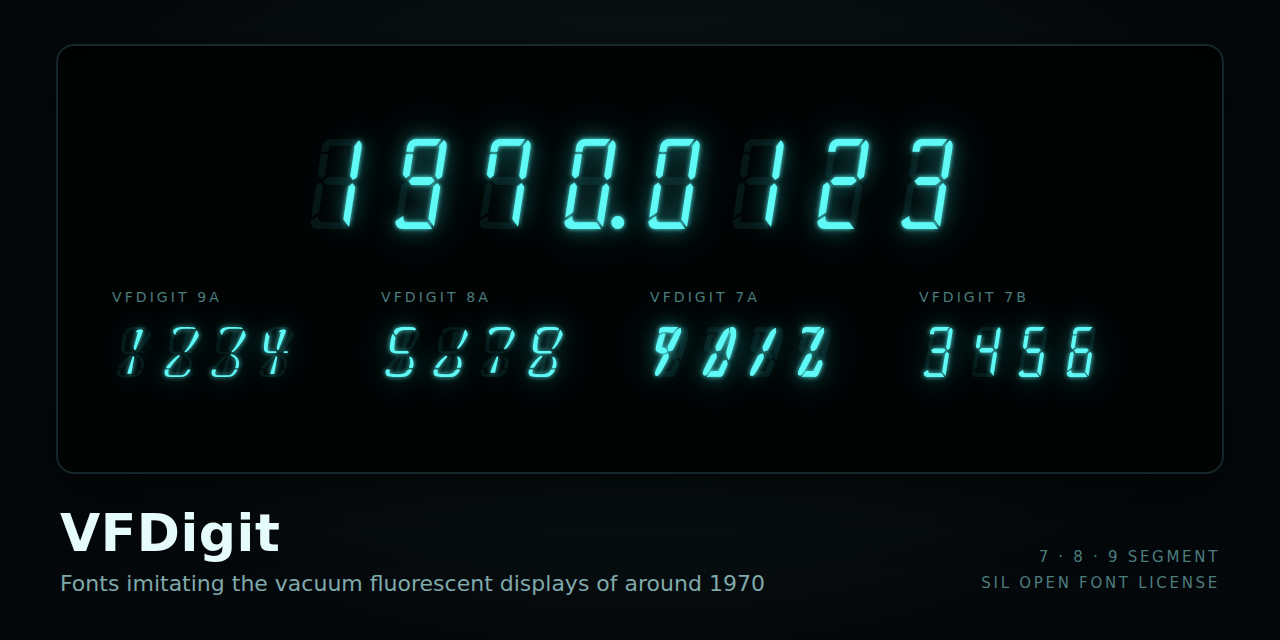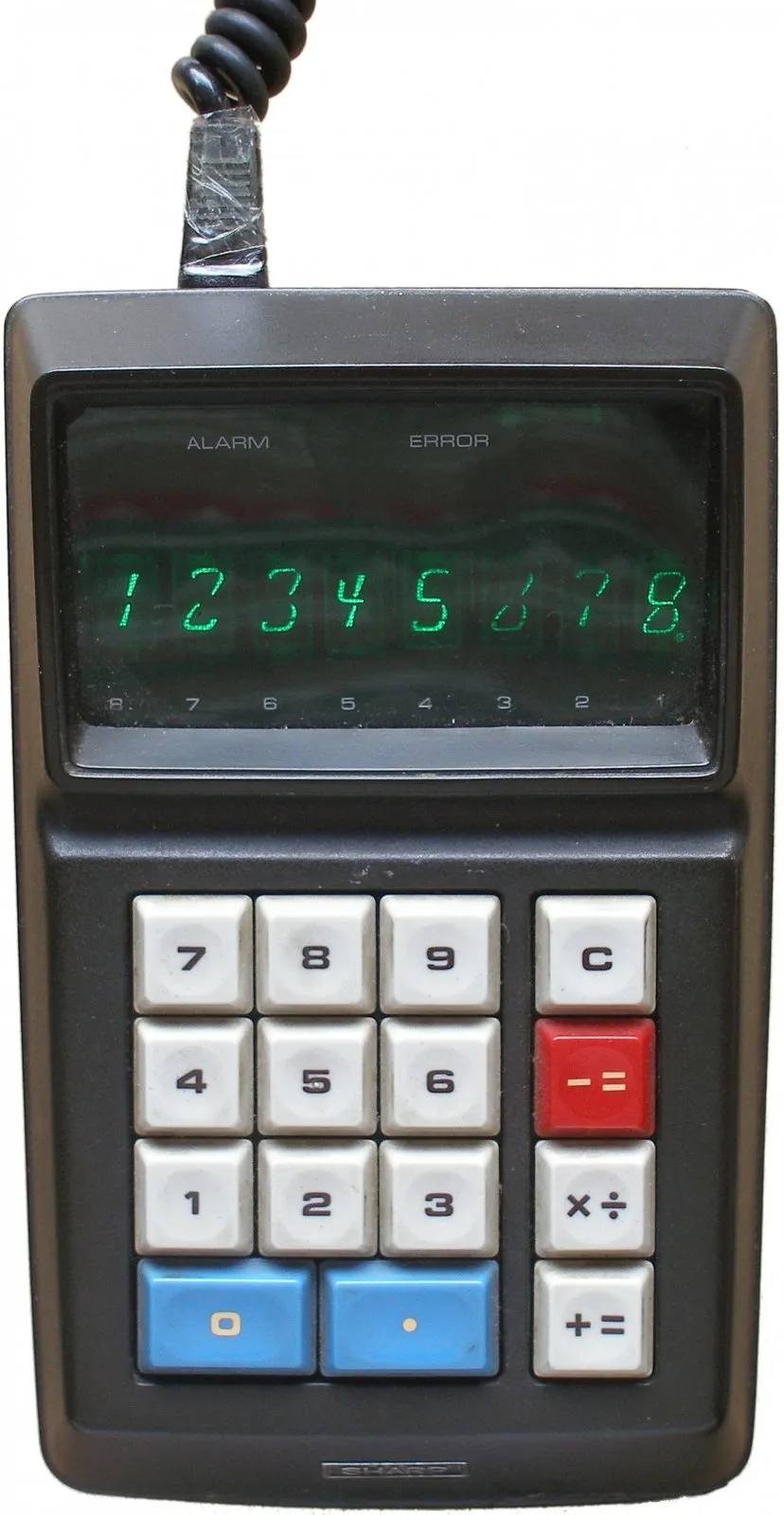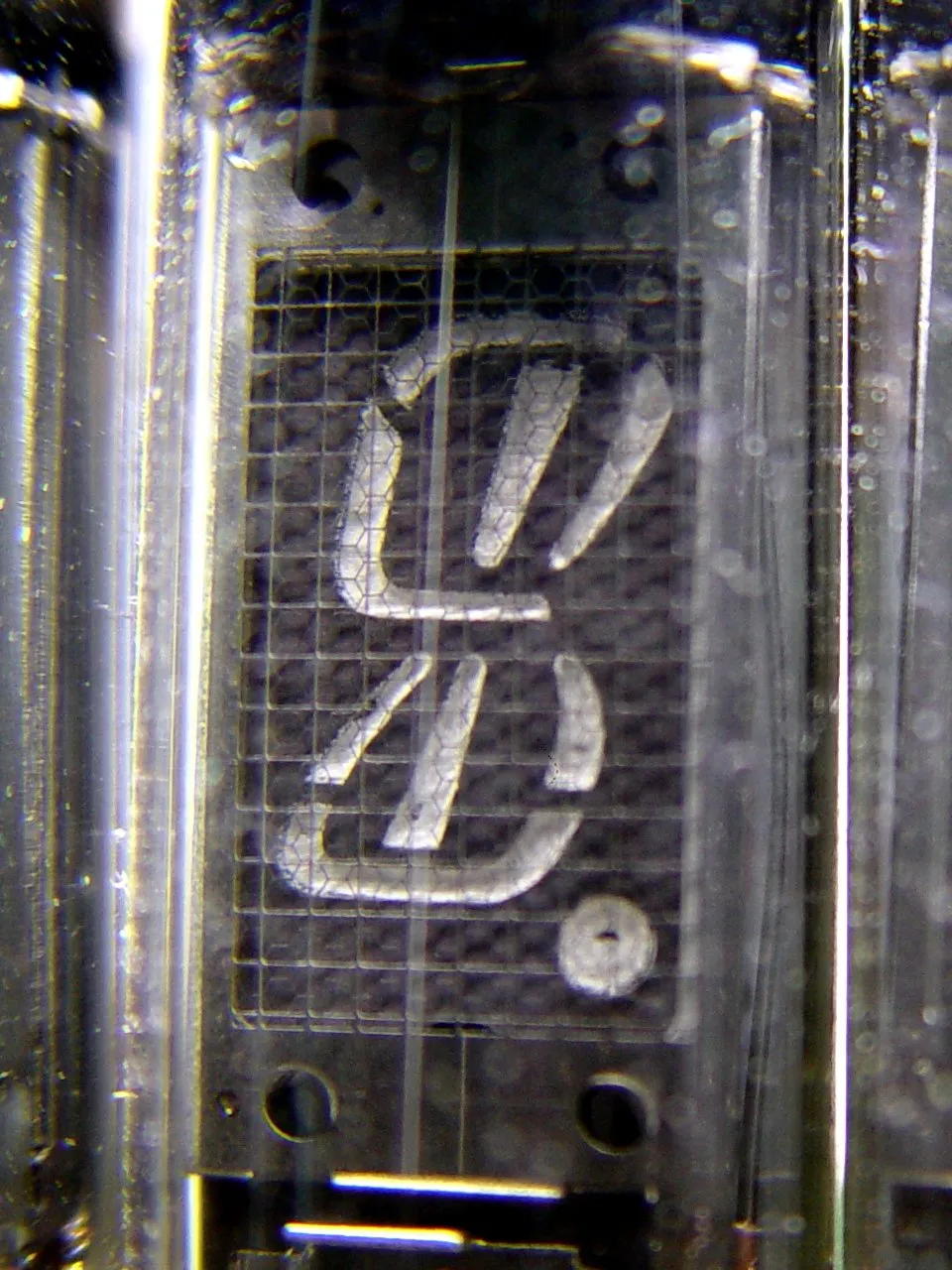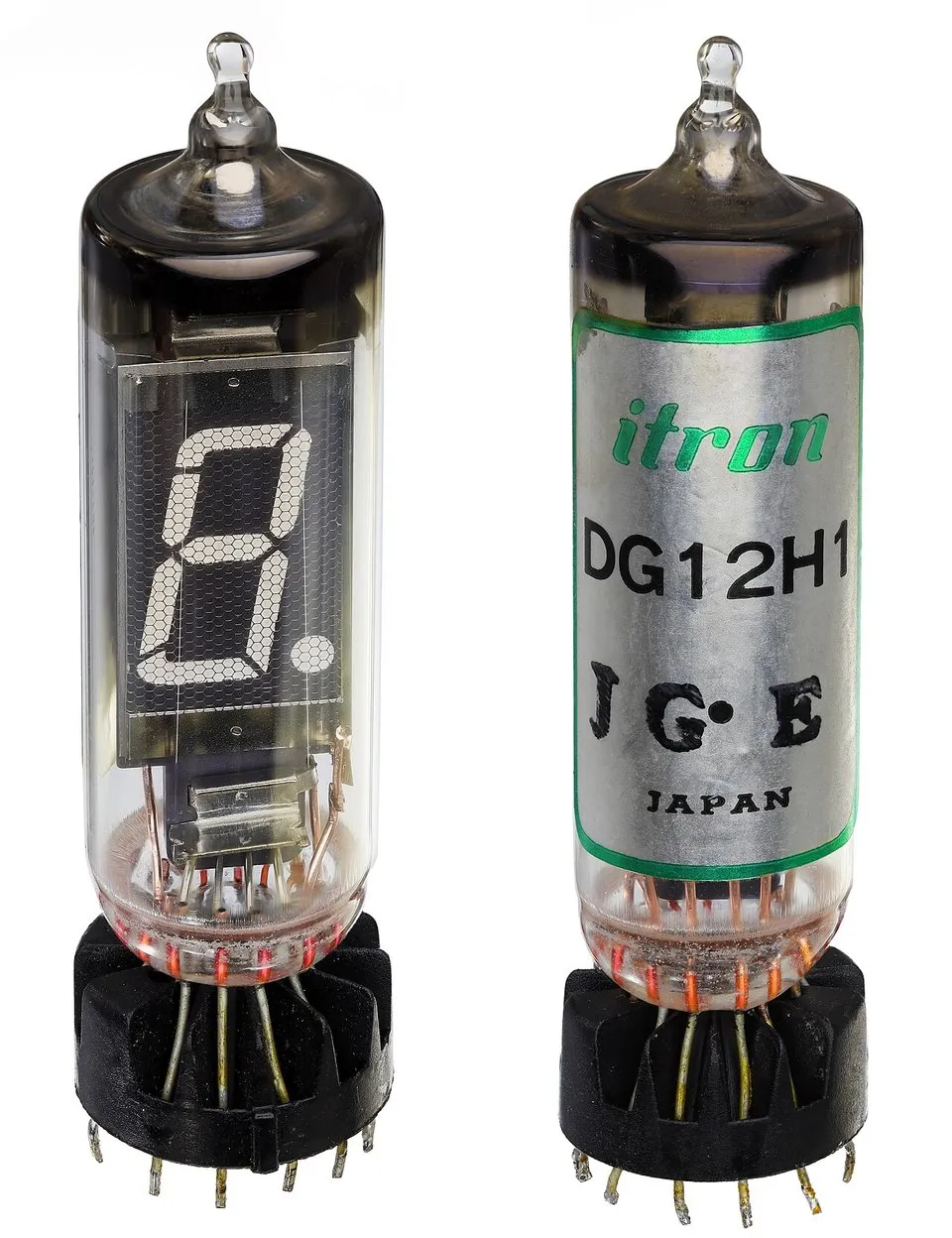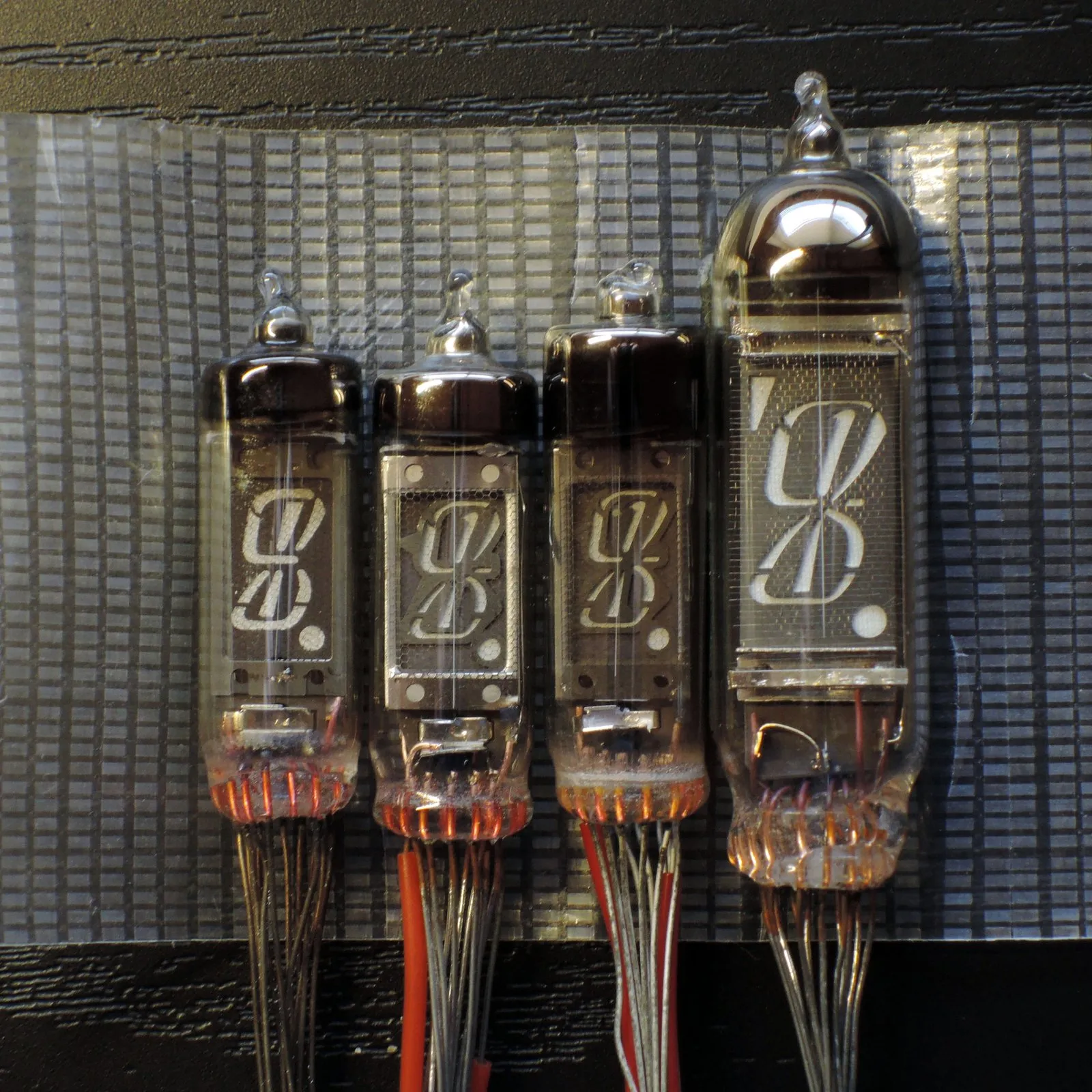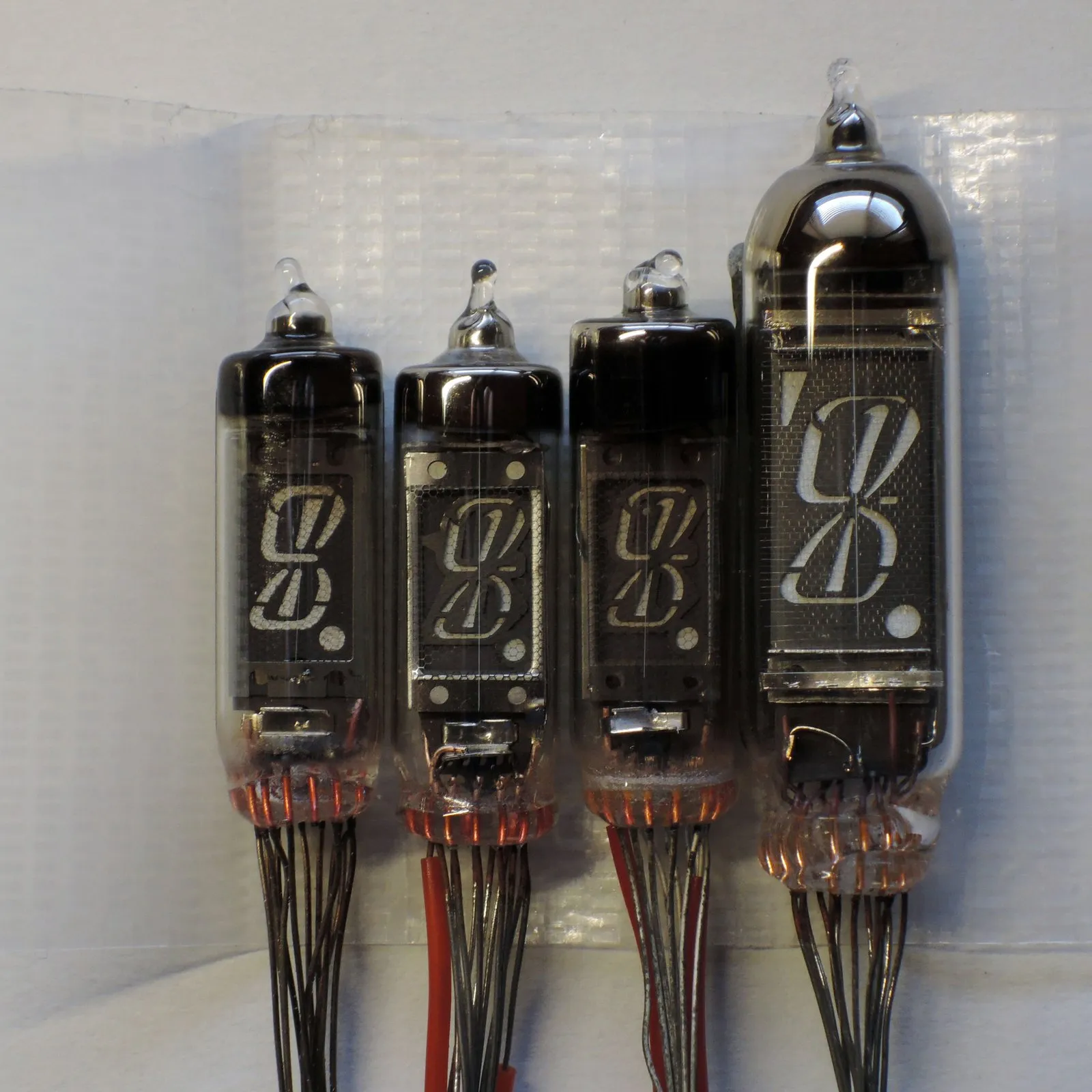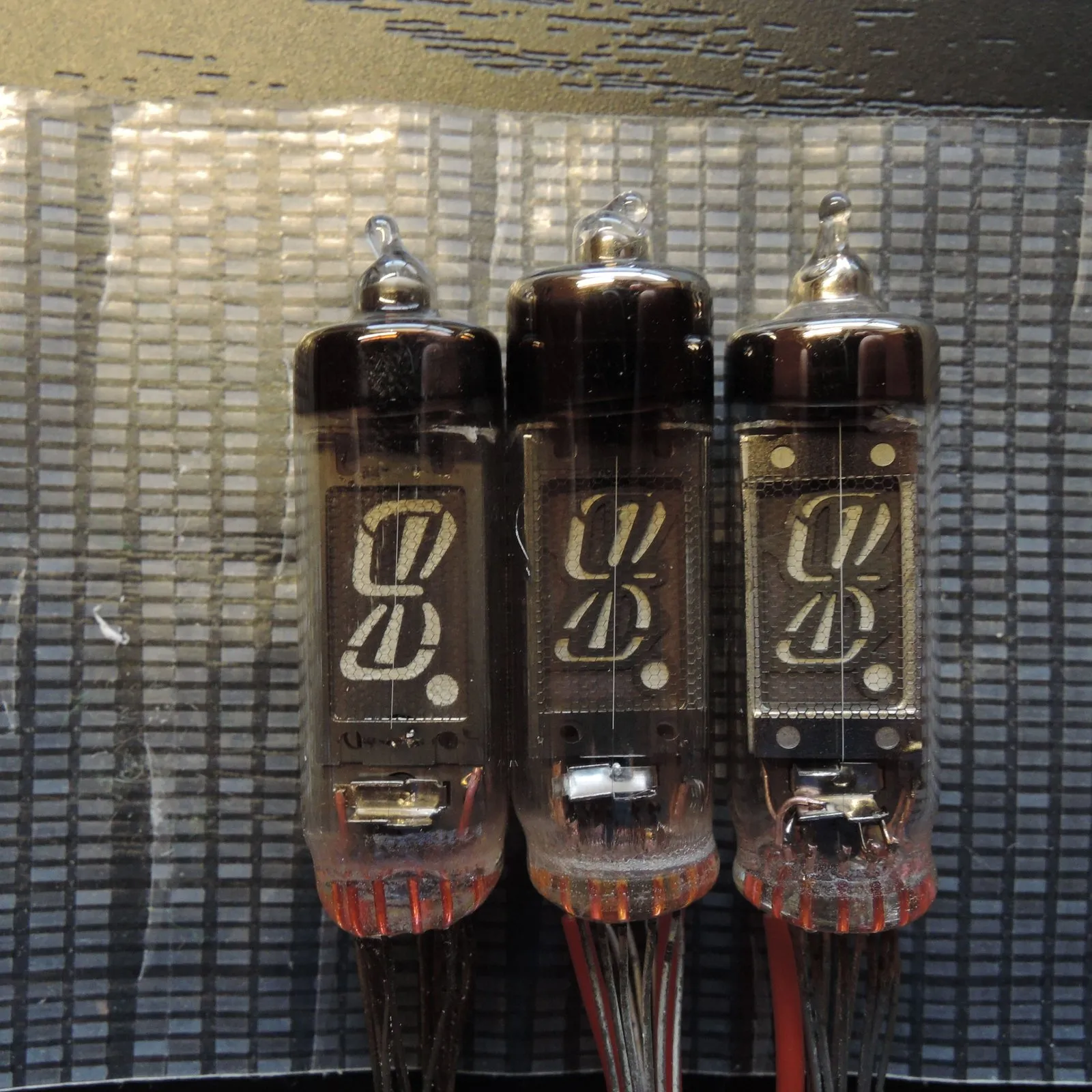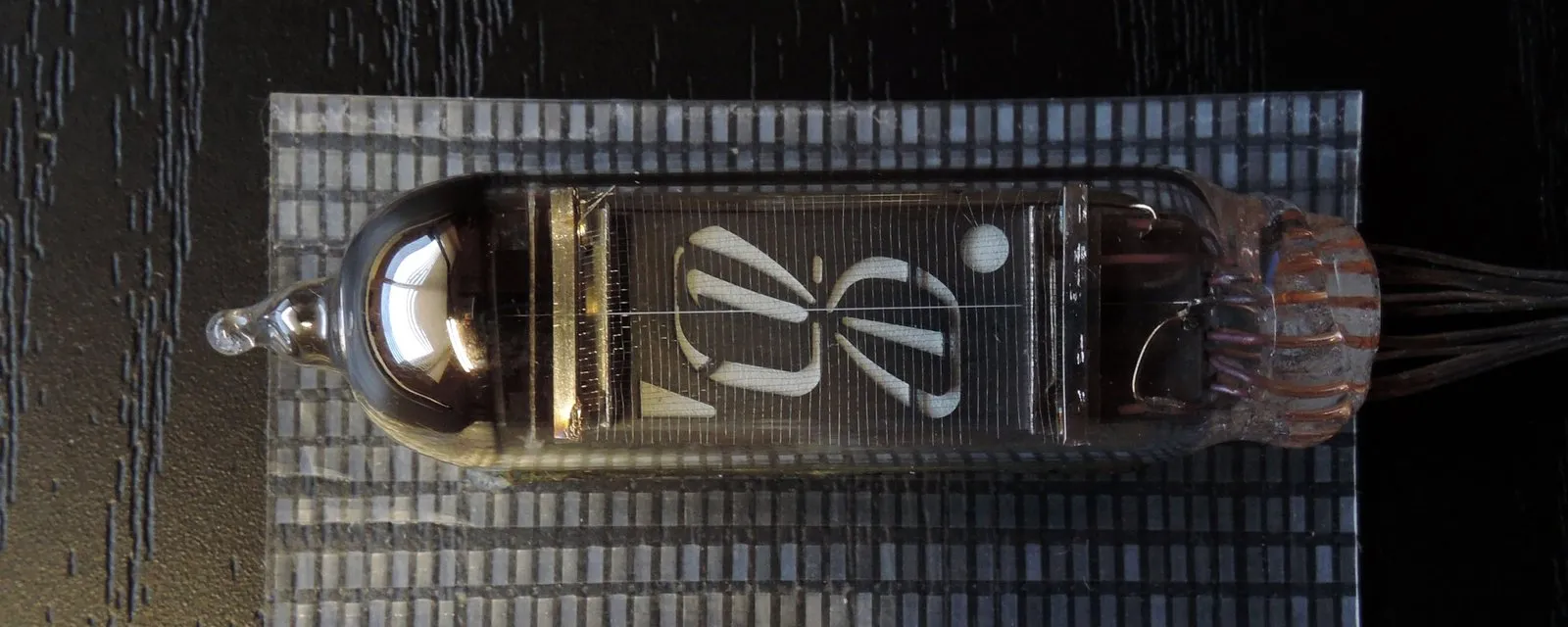
4書体の数字の見本です。画像ではなく Web フォントなので、文字を書き換えて試せます。
蛍光表示管(VFD)とは
蛍光表示管は、1966年に伊勢電子工業(現・ノリタケ伊勢電子)の中村正らが発明した日本発の表示技術です1。
電卓の表示には、それまで米国製のニキシー管が使われていました。1967年12月、シャープ(当時は早川電機工業)が蛍光表示管を初めて搭載した電卓「CS-16A」を発売し2,3、その後の「電卓戦争」の時代に電卓の表示部として広く使われるようになりました1。需要が急増すると、伊勢電子工業は VFD の特許を日本電気(NEC)と双葉電子工業にライセンスし、両社も VFD を生産しました3。
VFDigit は、この時代の電卓の VFD に表示された数字の書体を模しています。書体ごとに、元になった VFD のセグメント(数字を形づくる発光部分)の数と配置が異なります。
VFDigit 9A
シャープ(当時は早川電機工業株式会社4)が1967年12月に発売した電卓「COMPET 16(CS-16A)」5 などで使われた VFD「DG12B」を模したフォントです。DG12B は伊勢電子工業が最初に量産した VFD で、早川電機工業は1967年9月に CS-16A への採用を決めました3。日本電気製や双葉電子工業製の同等の VFD
数字部分は 9セグメントで、「4」のときにしか点灯しないセグメントがあります。
- カンマと小数点(ピリオド)は、数字と組み合わせたときに合字(リガチャー)となり、VFD と同じ位置に表示されます。
「6」には別の形も用意しています。OpenType の文字異体(Character Variant)の cv01 を有効にすると切り替わります。上が通常の形、下が cv01 の形です。
この書体に魅せられて、LED で再現しようとしている人もいるようです(Beautiful Display | Hackaday.io)。
VFDigit 8A
シャープの電卓「EL-8(通称 ELSI-8)」などで使われた VFD を模したフォントです。EL-8 の発売時期は、資料によって1970年7とも1971年初頭8ともされています。VFD は伊勢電子工業の Itron「DG10L」です7。「DG10L2」という型番の同型
数字部分は 8セグメント8で、DG12B の 9セグメントから「4」専用のセグメントがなくなっています。DG12B より小さい VFD で、同じ大きさにそろえると少し太い書体になっています。
- 元の VFD にはカンマ付きのものはないようですが、VFDigit 9A と同じカンマのグリフを収録しています。
- 小数点(ピリオド)とカンマは、数字と組み合わせたときに合字となり、VFD と同じ位置に表示されます。
VFDigit 9A と同じく、「6」の別の形を cv01 に割り当てています。上が通常の形、下が cv01 の形です。
VFDigit 7A
1969年に発売されたオムロン(当時は立石電機株式会社10)の電卓「OMRON 1210」11 などで使われた VFD の書体を模したフォントです。OMRON 1210 の表示管は手書き風の独特な書体で、オムロン独自のもの(オムロン製かもしれない)とされています12。
VFDigit 7A は、VFD「DG10H」(NEC 製13)の書体を元にしています。Old Calculator Web Museum に載っている OMRON 1210 の写真12 では表示管に「123456789012」が表示されていて、DG10H の数字と見比べると同じ形に見えます。ただし、OMRON 1210 の表示管が DG10H だったのか
数字部分は 7セグメントですが、一般的な 7セグメントとは配置が異なります。
- 小数点(ピリオド)は、数字と組み合わせたときに合字となり、VFD と同じ位置に表示されます。
VFDigit 7B
VFD の DG12H・DG12H1・DG10A の書体を模したフォントです。いずれも伊勢電子工業(Itron)製です14,15,16。一般的な 7セグメントと同じ配置で、斜体になっており、上端と下端のセグメントの左端が湾曲しているところが特徴です。
数字のほか、7セグメントで表現できる英字と記号も収録しています。英字は Seven-segment display character representations、記号は Seven-segment display を参考に割り当てています。
- 小数点(ピリオド)は、数字と組み合わせたときに合字となり、VFD と同じ位置に表示されます。
- 「=」は上付き文字(OpenType の sups)にすると上付きの「⁼」になります。
「0」「1」「6」「7」「9」と小文字「i」には別の形も用意していて、cv01 を有効にすると切り替わります。上が通常の形、下が cv01 の形です。
写真の大きい VFD が DG12B で、小さい方は類似した書体の VFD(型番不明)です。写真提供: VFDふぁん(画像をクリックすると原寸で開きます)
制作について
作ってみましたが、VFD の実物はそれなりの大きさ(2cm 前後)があるためか、PC で通常の文字として表示するには細く小さくなってしまいます。また、昔の電卓に使われていた書体という背景を共有していないと、意味の分からないフォントだと思います。デザインが微妙なところもあるので、気が向けばアップデートするかもしれません。